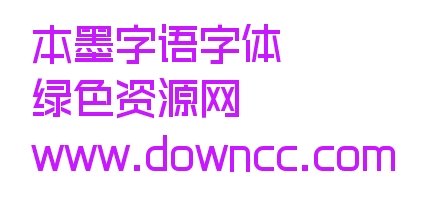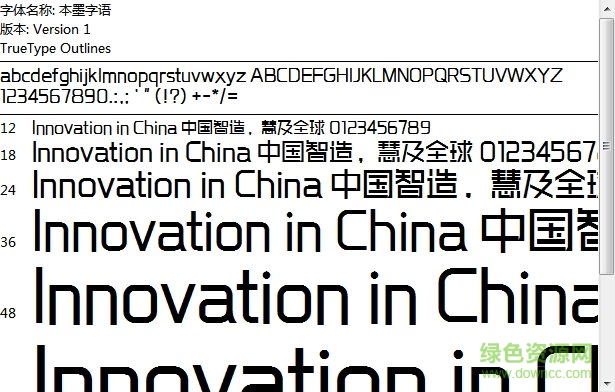
本墨字語(yǔ)在構(gòu)造上兼具本墨詠黑和本墨陳黑的字體特色,字跡深沉而莊嚴(yán),適用于嚴(yán)謹(jǐn)內(nèi)容或重要文字通知,給人清晰直觀的視覺(jué)呈現(xiàn),綠色資源網(wǎng)獨(dú)家推薦!
本字庫(kù)中文以國(guó)家GB2312-80標(biāo)準(zhǔn)設(shè)計(jì)制作,中文字?jǐn)?shù)6763個(gè),另包含ASCII常用字符150個(gè)。
本墨字語(yǔ)是本墨字庫(kù)最新推出的黑體字體,字跡清爽而端正嚴(yán)明,沒(méi)有多余的點(diǎn)綴,筆畫(huà)正直更顯大氣,運(yùn)用在平面設(shè)計(jì)、排版印刷等場(chǎng)合再合適不過(guò)!